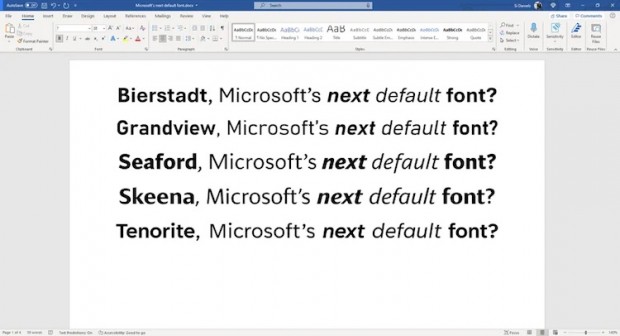
В следующем году Microsoft решила поменять шрифт Office, используемый по умолчанию. Компания попросила пользователей помочь ей с выбором, причём это не будет один из существующих шрифтов. Хотя в Office доступно более 700 вариантов шрифтов, Microsoft заказала создание пяти новых, один из которых и заменит стандартный Calibri, использующийся в течение почти 15 лет.
Пять новых шрифтов без засечек выполнены в разных стилях, включая традиционный, современный, а также вдохновлённый немецкими дорожными и железнодорожными знаками. Microsoft начинает собирать отзывы об этих пяти начертаниях сегодня и планирует установить один из них в качестве нового шрифта Office по умолчанию в 2022 году.
Tenorite является наиболее традиционным из пяти шрифтов. Он похож на более современную версию Times New Roman, созданного несколько десятилетий назад. Он выделяется широкими символами с чётким начертанием. Skeena вдохновлён различными периодами дизайна шрифтов. Он демонстрирует большую разницу толщины тонкой и толстой частей буквы, а также очень чёткие кривые линии некоторых символов.
Bierstadt вдохновлён швейцарской типографикой средины 20 века. Он имеет чёткие очертания символов и обладает некоторым сходством с хорошо знакомым многим пользователям Helvetica. Seaford выглядит наиболее привычно из всех новых шрифтов. Дизайнеры заявляют, что черпали вдохновение в старых креслах, а пользователи отмечают, что Seaford лучше других новых шрифтов подходит для чтения длинных документов.
Наконец, Grandview, вдохновлённый классическими немецкими дорожными и железнодорожными знаками, выглядит наиболее интересно. Он очень разборчив и в теории хорошо подходит для работы с большими объёмами текста.
Microsoft добавляет эти пять новых шрифтов в Microsoft 365, чтобы пользователи могли опробовать их, прежде чем будет выбран новый шрифт по умолчанию. Следующие несколько месяцев компания собирается потратить на оценку этих шрифтов и сбор отзывов о них. После того, как окончательное решение будет принято, новый шрифт по умолчанию появится в приложениях Microsoft Office в 2022 году.